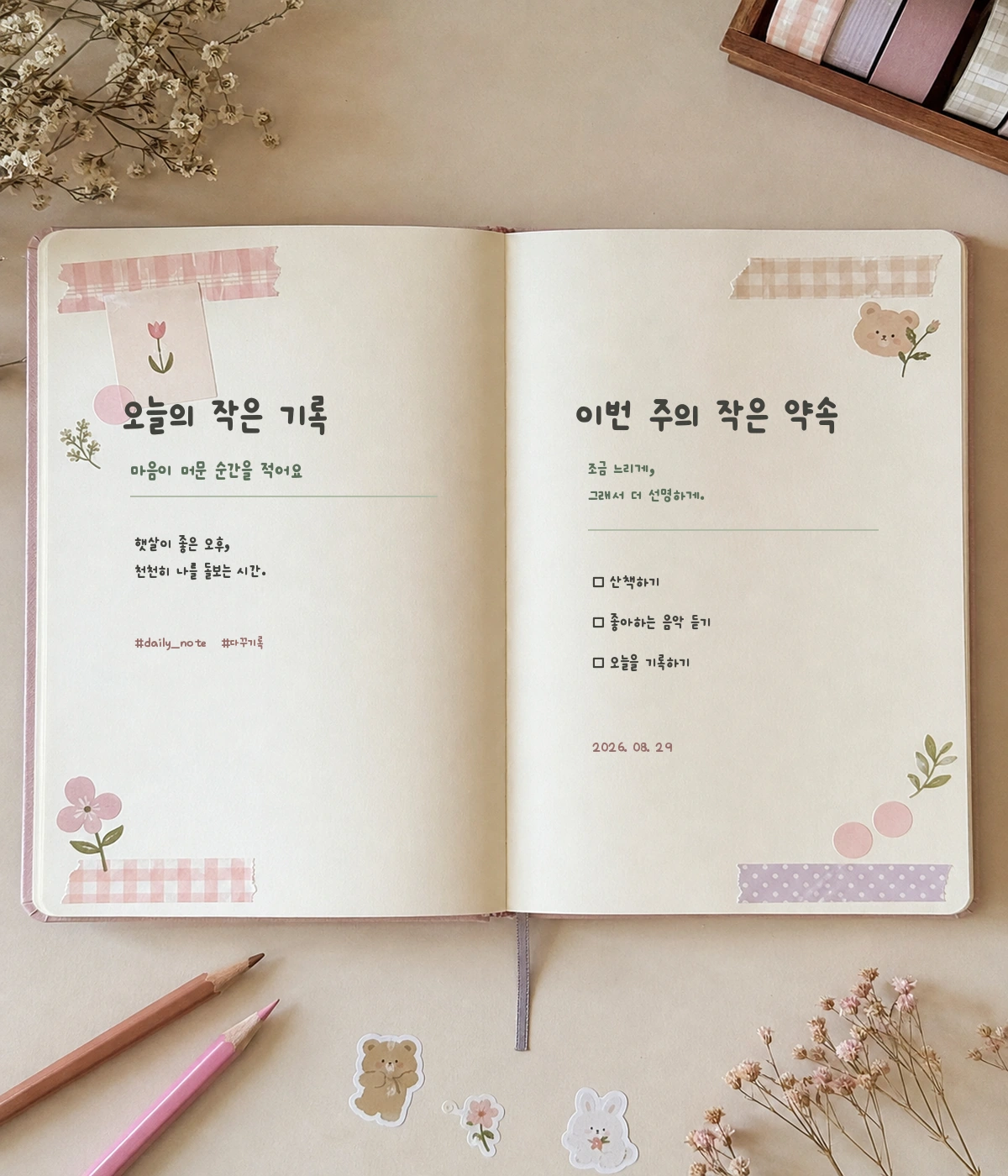
온글잎 레이나 — 온글잎에서 배포하는 무료 폰트입니다. 다이어리에 직접 써 내려간 듯한 단정하고 아기자기한 손글씨체
아이패드로 다이어리를 꾸미는 크리에이터 레이나 님의 손글씨로 만든 서체입니다. 온글잎 서체 가운데 글씨 주인이 분명히 밝혀진 드문 경우인데, 본인이 직접 남긴 소개가 있기 때문입니다. 아이패드로 다이어리를 꾸미는 크리에이터라고 자신을 소개하면서 자기 손글씨로 폰트를 만들었고 여러분의 아이패드 생활에도 도움이 되길 바란다고 적었습니다. 2022년에 나왔습니다.
조형 설명은 따로 없어 파일을 보고 적습니다. 받침이 붙을 때 글자 높이가 달라지는 탈네모틀이고 낱자는 가로로 퍼져 있어, 다이어리에 적어 내려간 글씨의 인상이 남아 있습니다.
굵기는 하나이고 한글은 2,786자입니다. 완성형 11,172자를 다 담은 것이 아니라 흔히 쓰는 글자 위주로 골라 넣은 것이라 드문 음절은 빠질 수 있습니다. 다이어리나 짧은 메모, 감성 문구에 어울리고 어떤 글자가 올지 모르는 자리에는 미리 확인하고 쓰세요. 상업적으로 쓸 수 있지만 폰트 수정은 금지됩니다.